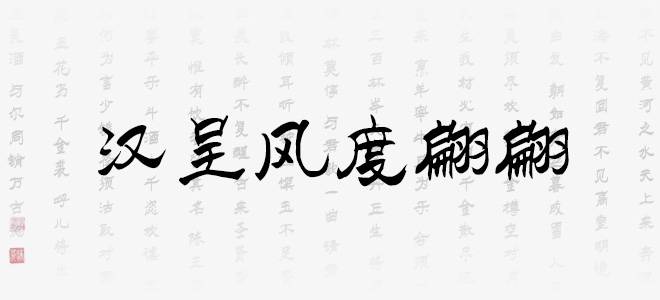
漢呈風(fēng)度翩翩字體是漢呈字庫推出的一款個性藝術(shù)字體,字體字型非常的風(fēng)度翩翩、有意思,具有很好的視覺感,適合藝術(shù)設(shè)計、平面宣傳設(shè)計、網(wǎng)頁設(shè)計,書法字帖等領(lǐng)域具有很好的視覺感,適合藝術(shù)設(shè)計、平面宣傳設(shè)計、網(wǎng)頁設(shè)計,書法字帖等領(lǐng)域,歡迎喜歡漢呈風(fēng)度翩翩字體的朋友前來下載使用。
漢呈風(fēng)度翩翩